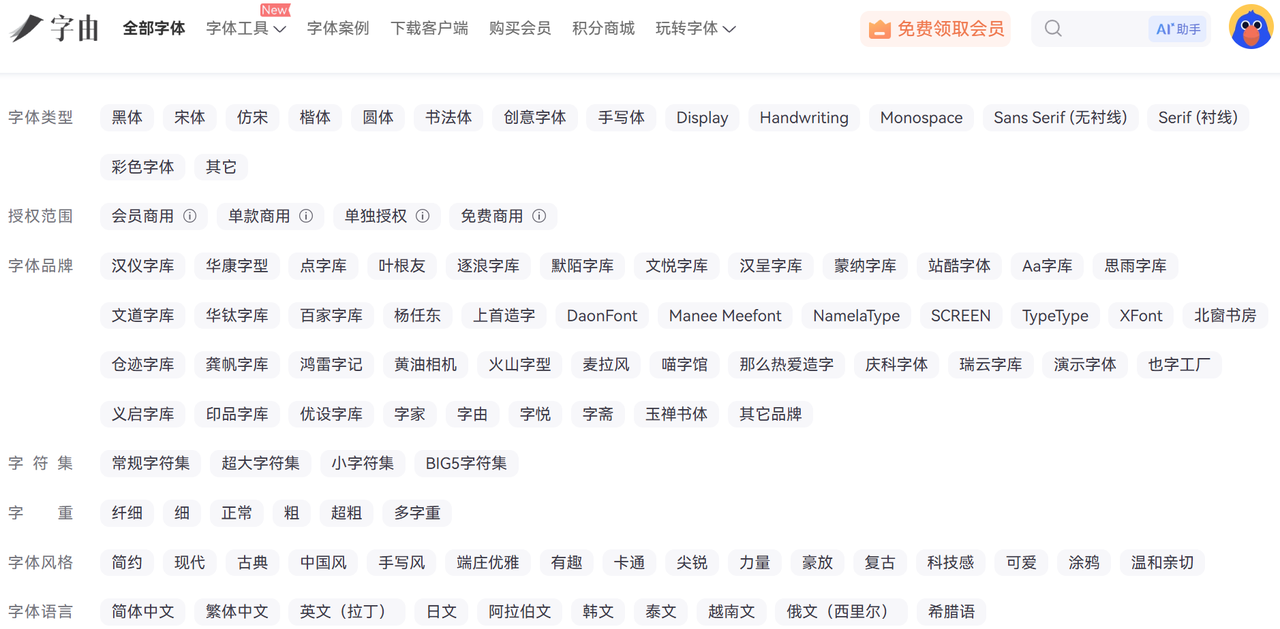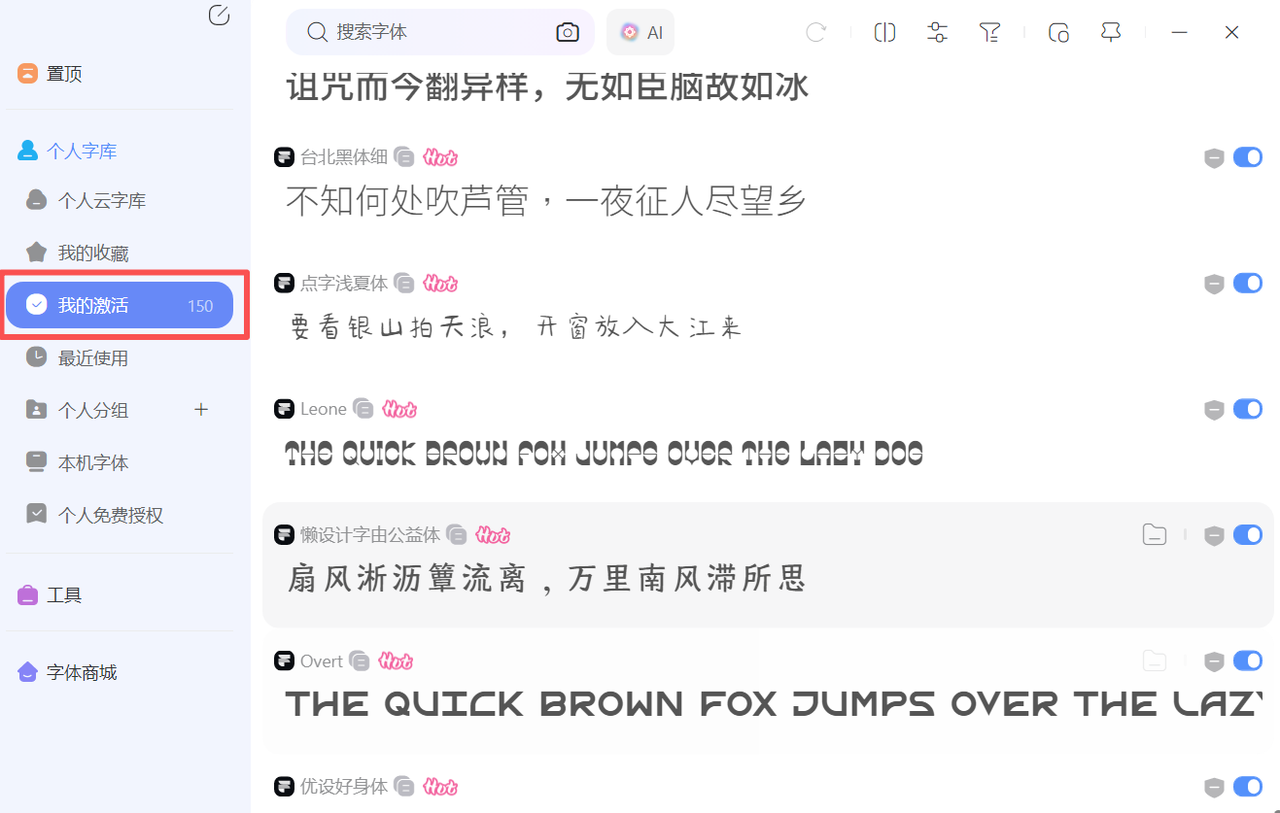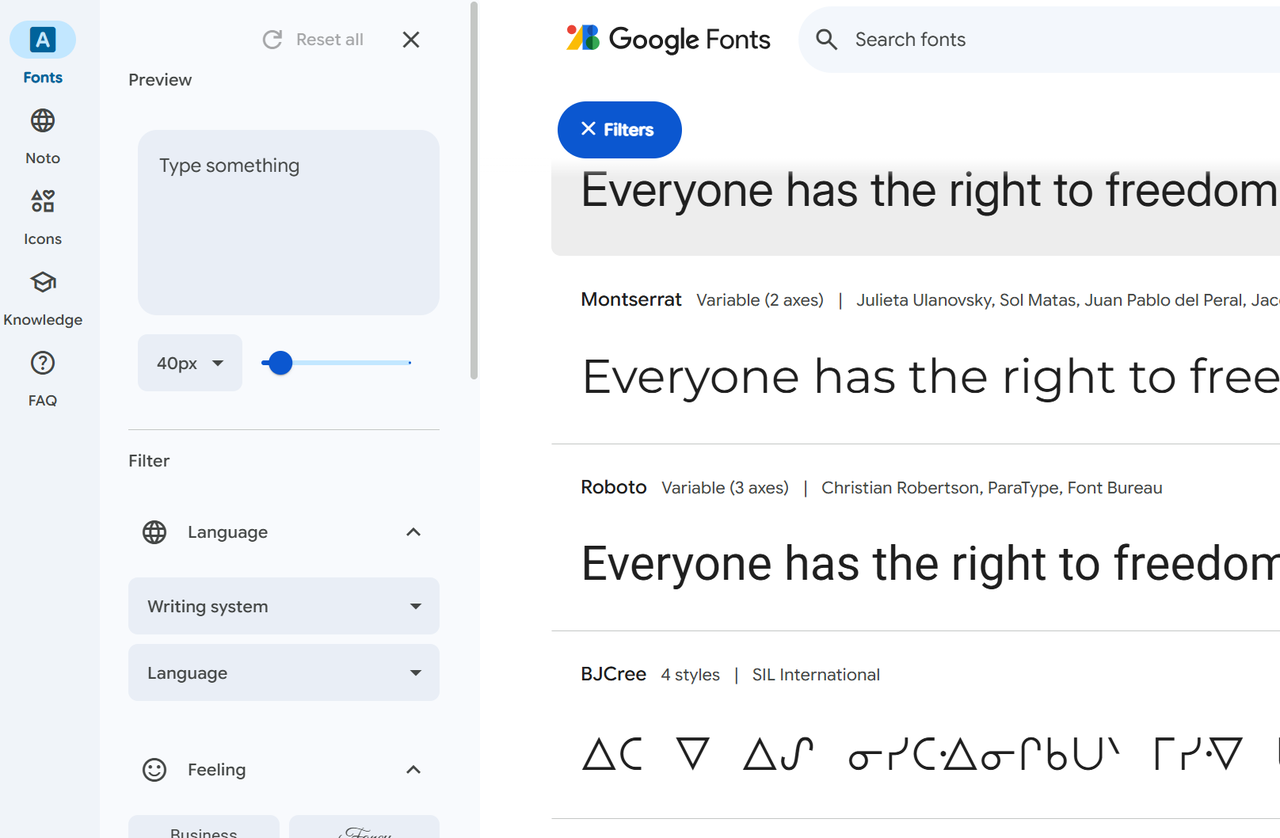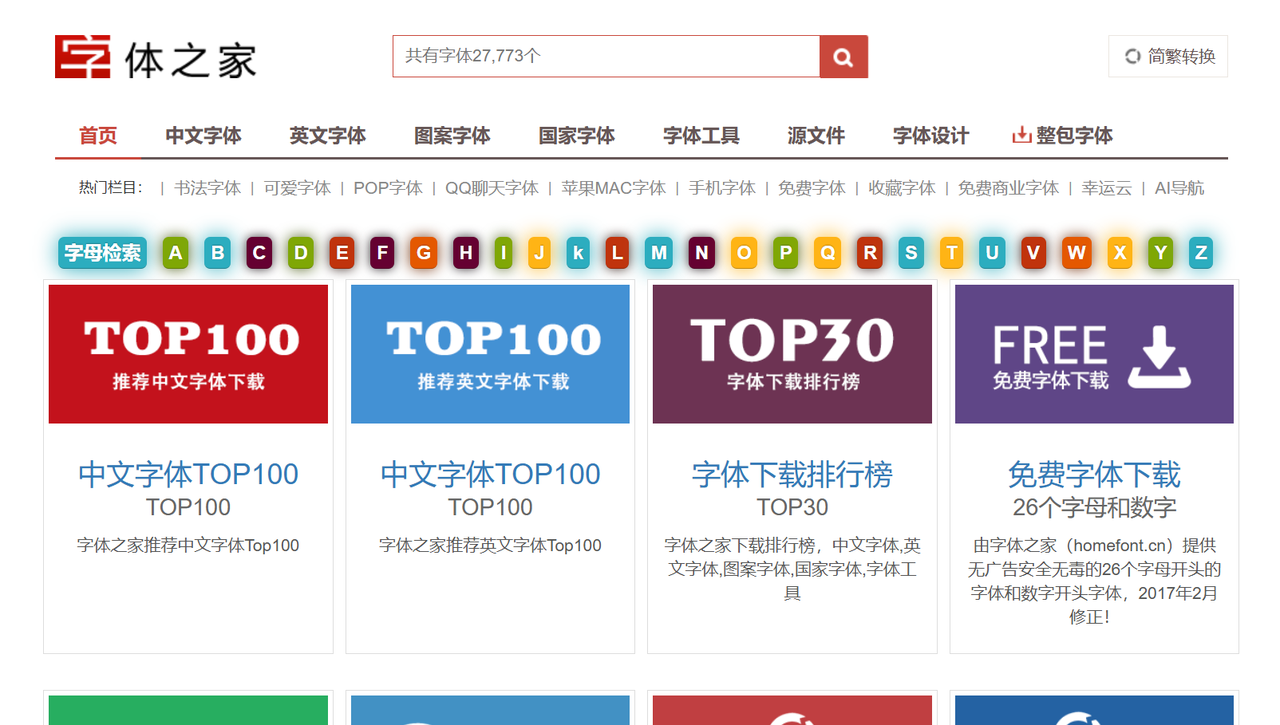
免费字体库在线下载,字由与5个优质平台推荐
做设计的时候,我发现字体的选择很重要。不管是做网页、海报还是写文稿,字体都直接影响作品的风格。一开始,我总是在网上零散地找字体资源,每次都要检查有没有版权问题。有些字体虽然漂亮,但不能商用,或下载不方便。
后来我把关注点从字体到了字体平台,有些网站还允许字体在线预览,减少了来回转换的麻烦。接下来,我会详细介绍自己常用的字由平台,以及其它几个优质平台,希望你也能用得顺手。
在众多字体库中,我首推字由。它是我平时最常用的平台之一。字由的界面简洁,操作逻辑清楚,字体分类科学。无论是中文还是英文字体,都有详细的标签、筛选和预览功能。每款字体都有清楚的用途说明,非常适合设计、视频、平面等不同场景。
字由的字体下载很方便。不用每一款字体都在线安装,通过字由客户端就可以一键激活使用,即便换了电脑也没关系,常用字体还是会保留在字由客户端中,对于经常需要更换字体的设计师来说,这一点太实用了。比如我就激活了 150 款字体,需要切换哪款,只需要在设计软件中选中文字,然后在字由客户端点击对应字体即可。
Google Fonts
Google Fonts是国外知名的字体库,收录大量开源字体,适合网页和各类设计应用。它提供简体、繁体、英文、日文等多语言选项。页面支持在线预览,能模拟不同字号和样式。字体使用说明清晰,商用无忧。我常在做英文网站、APP时用它来选配字体。
字体之家
字体之家以资源丰富著称,涵盖中文、英文字体及各类创意字体。它的页面布局简洁,支持字体样例在线生成,方便预览文字效果。每款字体都标示版权情况,可按需求筛选,非常适合设计师。
站长字体网
这个平台专注于字体整合与分类,提供多样字体下载包。适合网站、PPT、资料设计使用。操作简单,下载无需复杂注册。我经常用它抓取一批字体做初步筛选。
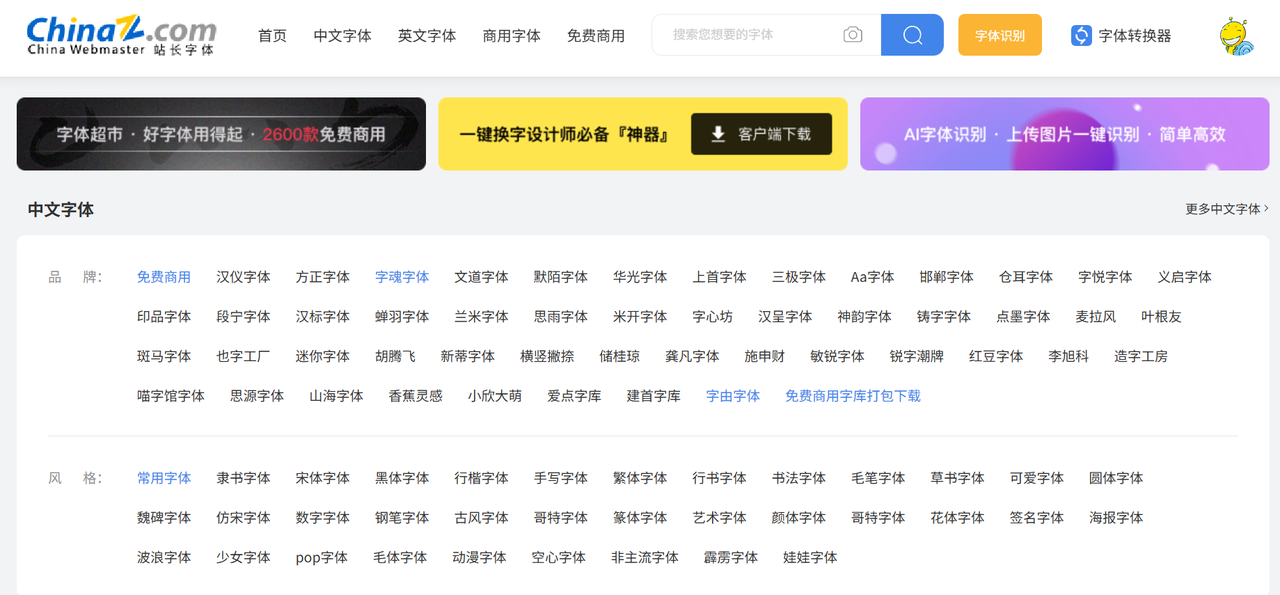
优设网
优设网作为设计资源聚合平台,专门分类整理了免费商用字体库。字体筛选详细,设计师推荐多,有丰富案例展示。适合综合查找、灵感挖掘与初学者体验。
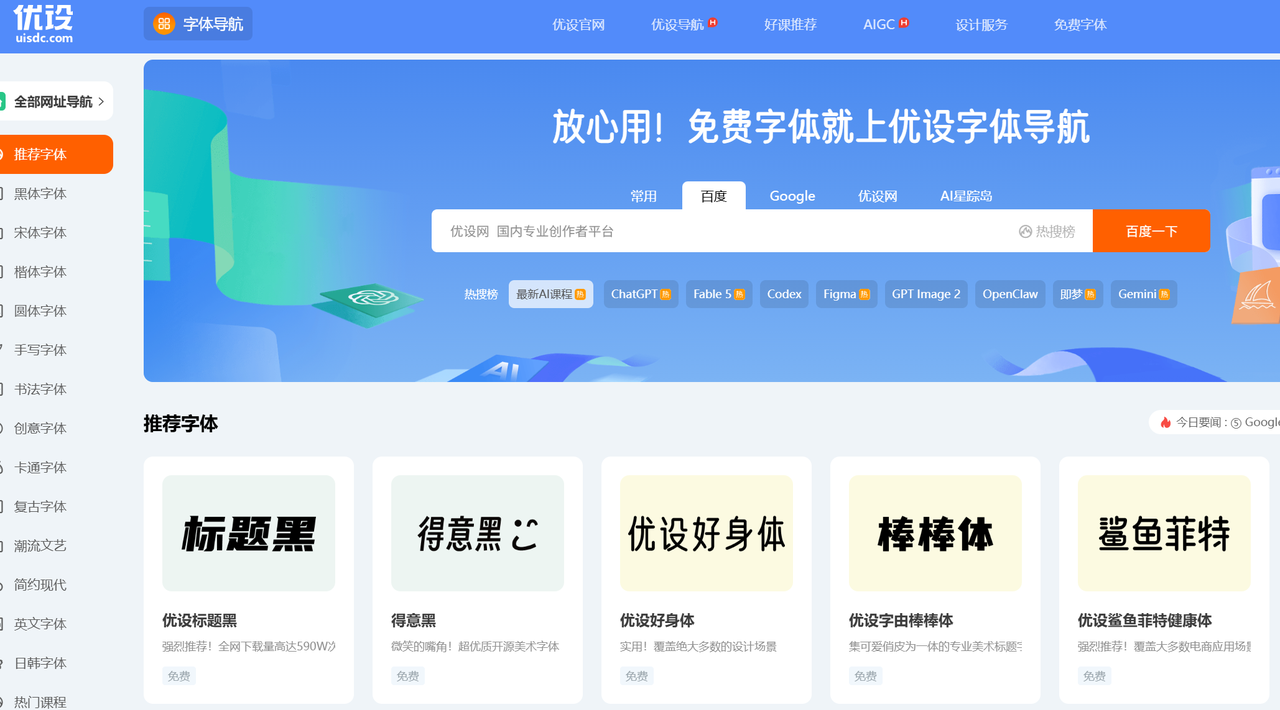
思源字体
思源字体由Google与Adobe共同推出,支持多种语言的开源字体。思源黑体、思源宋体等均为开源免费字体,官方提供下载,适合各类商业项目。字体风格简洁,显示效果良好。
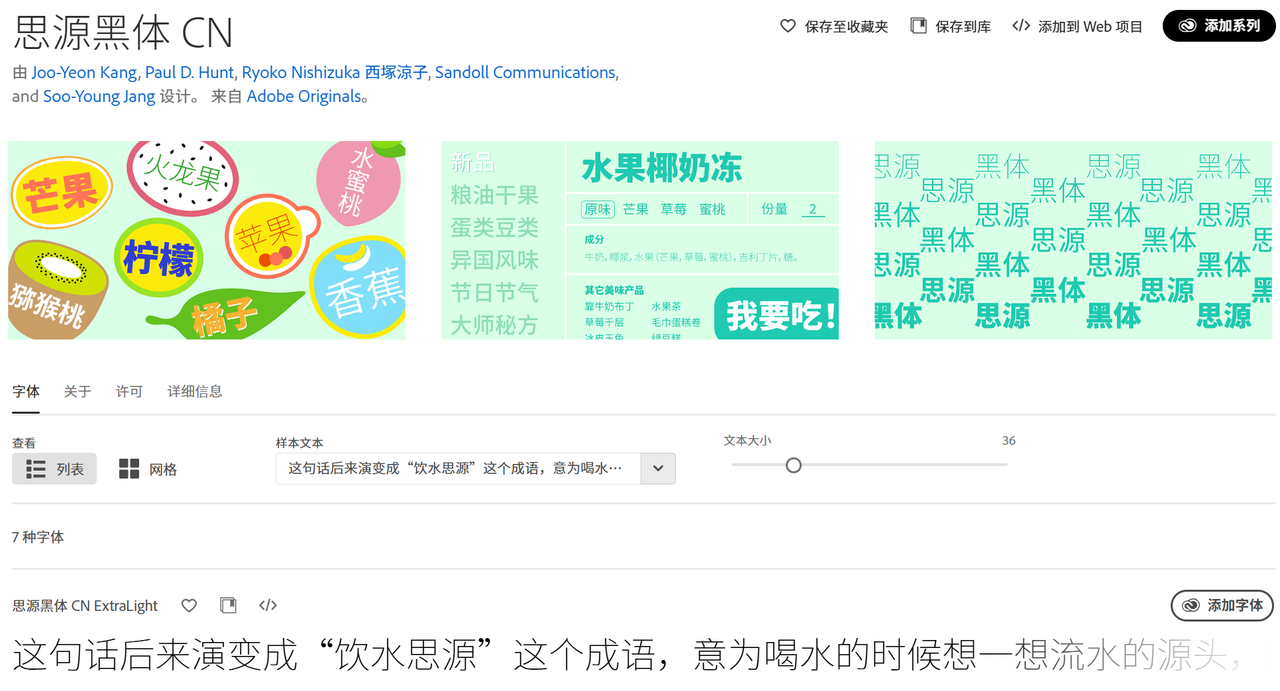
免费字体库使用小技巧
- 按需筛选:根据应用场景(如网页、海报、LOGO等)筛选合适字体。可以先在线预览,再下载使用。
- 多平台对比:不同字体库资源各有特色,结合多平台筛选,能让字体选择更充分。
- 关注更新:部分平台会定期更新新款字体,不妨关注动态获取新资源。
- 字体工具辅助:如字由、字体管家类平台还提供字体管理、转换、在线预览工具,值得试用。
个人建议
我曾经因为找字体耗费大量时间,也担心过版权纠纷。现在利用优质的免费字体库在线下载,我能轻松找到合适的字体方案。字体库平台的操作便捷让我有更多精力专注于设计本身。字体多样、授权清晰,每一次选择都带来新的灵感。
如果你正在设计项目或准备制作个人作品,建议你先收藏以上免费字体库平台。无论是字由还是Google Fonts,都能作为可靠的起点。学习使用这些平台的方法,会让你的设计效率和作品价值大大提升。